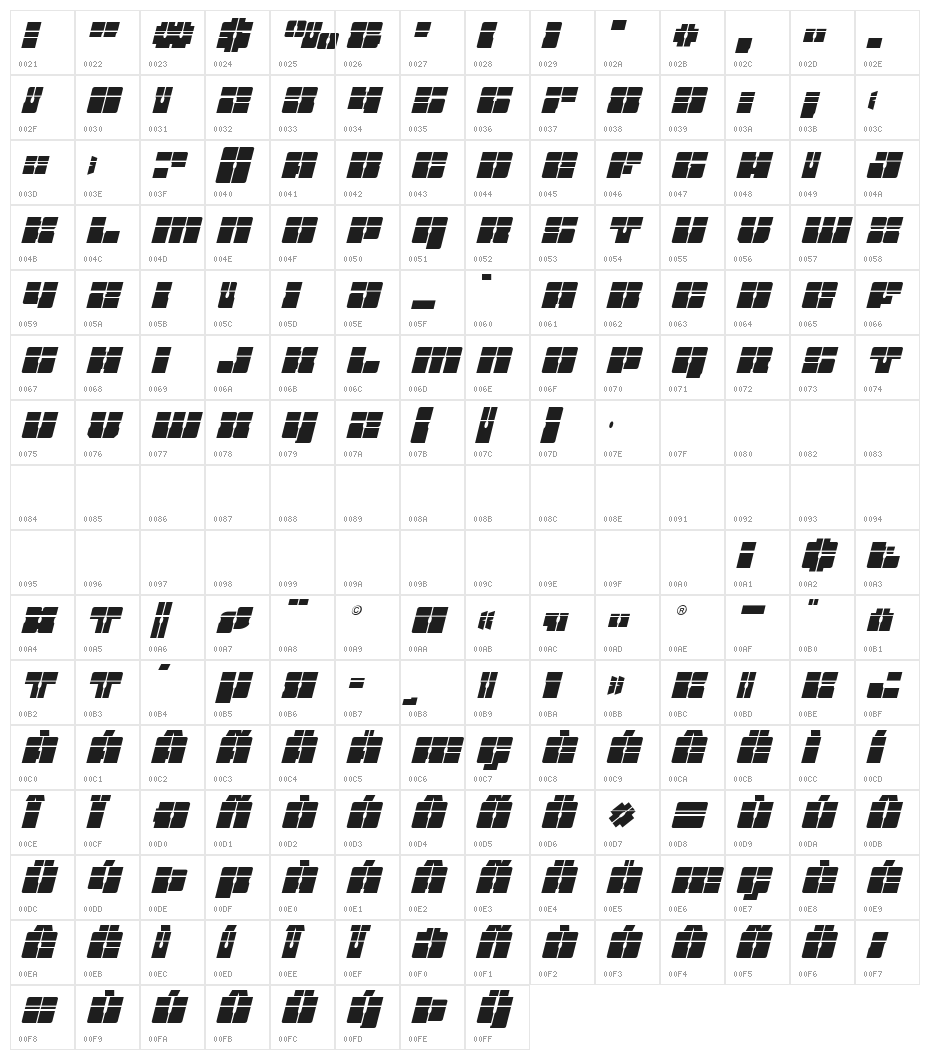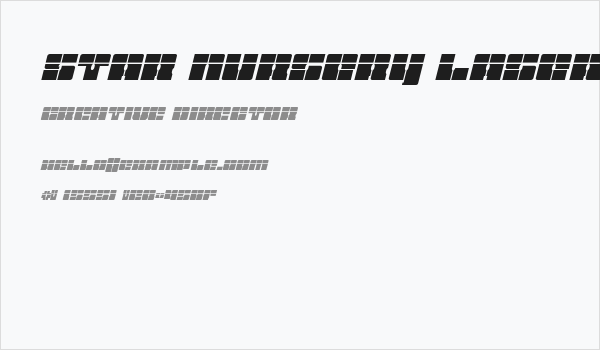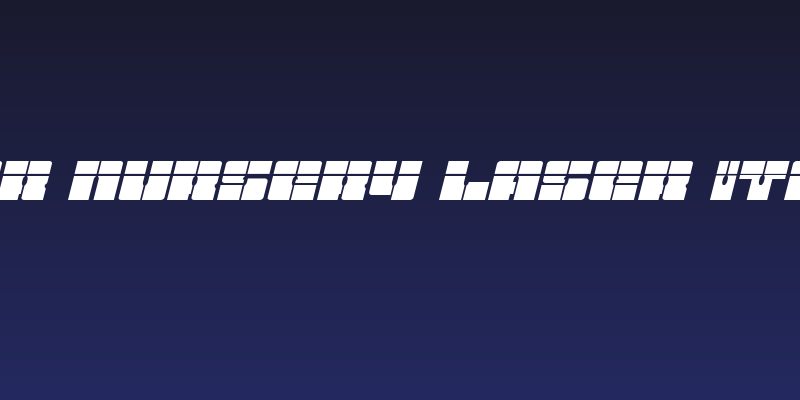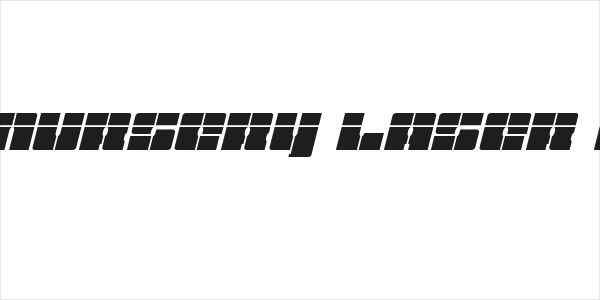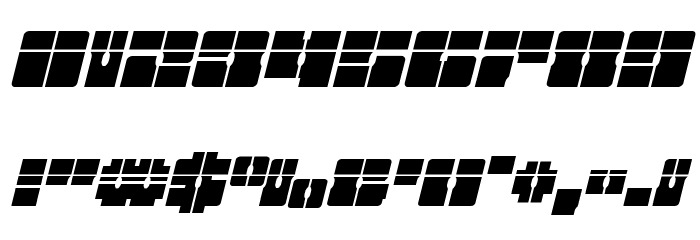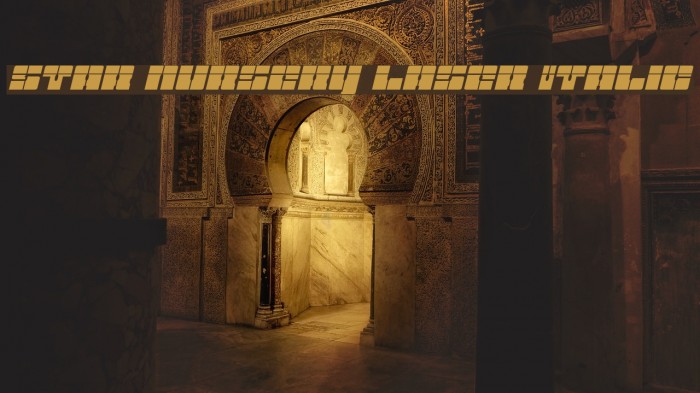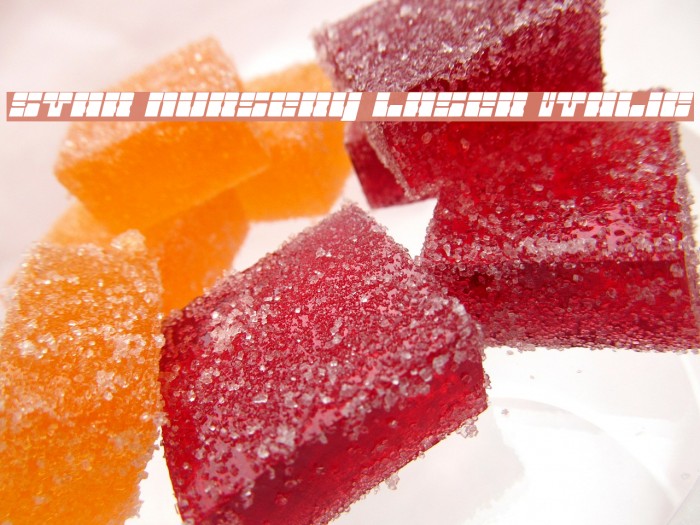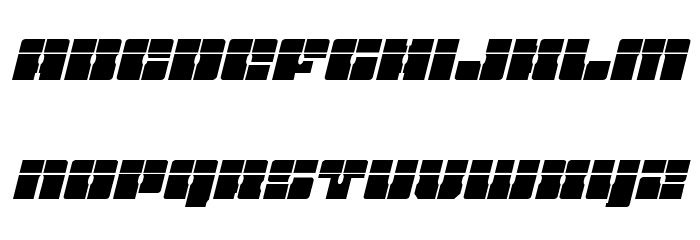
Star Nursery Laser Italic Font
| Proyectos propuestos | Ideal for sci-fi themed posters, video game titles, tech branding, and modern advertising campaigns. |